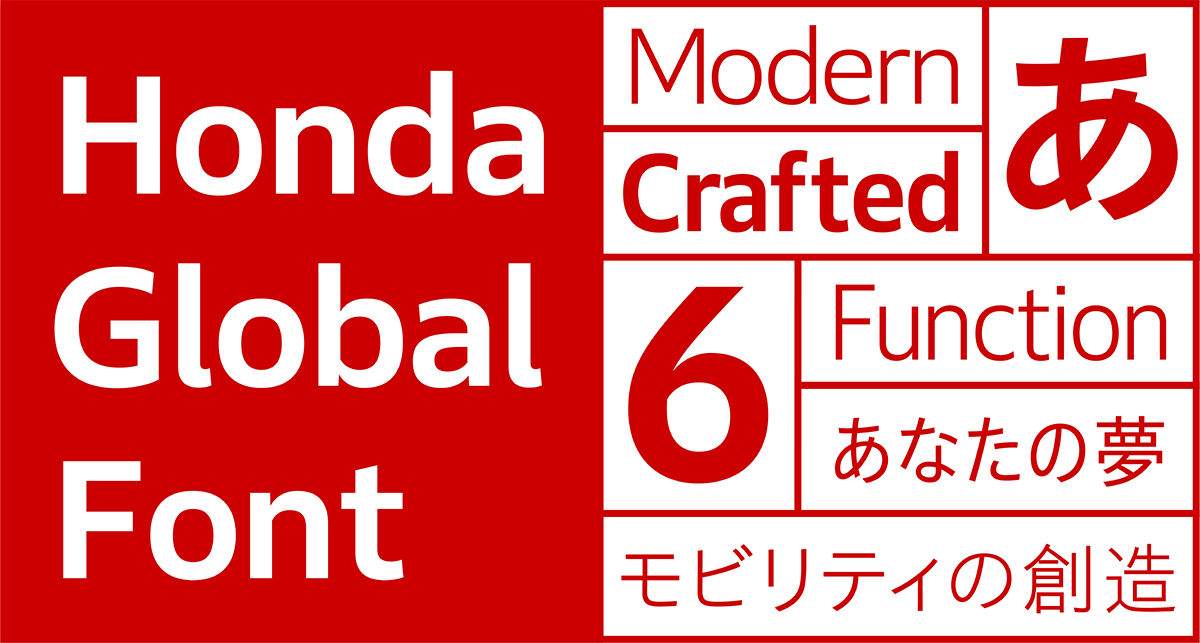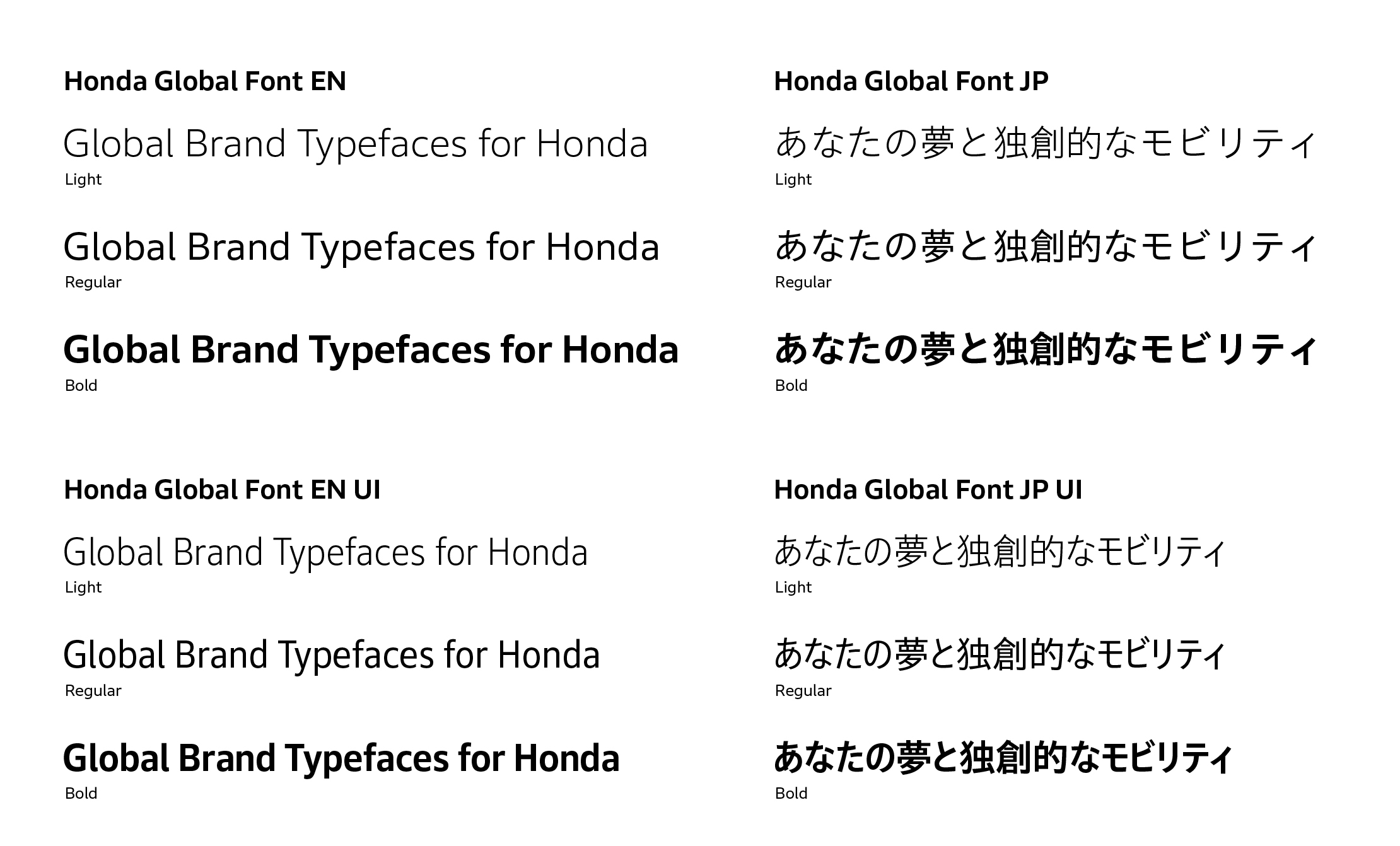
モリサワ 総合モビリティカンパニー Hondaのコーポレートフォント「Honda Global Font」ファミリーを開発
Hondaは、幅広いモビリティやサービスを世界中のお客様にお届けしている総合モビリティカンパニーです。100年に1度ともいわれる大きな変革期を迎えているなか、2001年に策定されたグローバルブランドスローガン「The Power of Dreams」を2023年に再定義し、改めて「Hondaのブランドマネジメントの起点」と位置付けました。夢のある商品・サービスをはじめとしたあらゆる企業活動を通して、この再定義に込めた想いを体現していくことで、よりHondaらしさを際立たせ、存在を期待される企業であり続けることを目指しています。
そして、このグローバルブランドスローガンを起点としたブランディングの一環としてコーポレートフォントの策定が検討され、多数のオリジナルフォント開発実績があるモリサワが、「Honda Global Font」ファミリーを開発・提供しました。「Honda Global Font」ファミリーの活用によって、Hondaブランドの発信の一貫性を高めるとともに、社内ブランディング意識の向上などが期待されています。
今回開発した「Honda Global Font」ファミリーは、欧文フォントの「Honda Global Font EN」と和文フォントの「Honda Global Font JP」、そして長体幅にしたUIフォントです。Hondaのブランドデザインを手掛けるブランド・コミュニケーションセンターのチームと、モリサワのプロジェクトメンバーが、両社の垣根を越えてアイデアを交わし合い、開発が進められました。
本フォントはHondaの人中心思想に基づいて、モビリティに求められる瞬間認知等の機能性を前提に、一人ひとりの強い意思を想起させるフォントとしてデザインされました。
欧文フォントのHonda Global Font ENは、モリサワの「Clarimo UD PE」をベースにカスタマイズしたサンセリフ体です。大きめの字面やオープンな開口部の処理によって、走行中での文字の瞬間的な認知のしやすさに配慮しています。また、安定感のある凛とした骨格と、勢いのある筆の運び、末端まで意識が通った丁寧な所作によって先進的かつこだわりを感じるモダンでクラフテッドな印象を作り出しています。
そして和文フォントのHonda Global Font JPは、モリサワの「あおとゴシック」をベースとしながら、有限会社字游工房の書体設計士 鳥海修氏が監修に携わり開発したゴシック体です。欧文と同じく視認性などの機能面に配慮しながらも、かなの横画に右上がりの傾斜を持たせることで、和文ならではの自然なリズムを表現しています。ストロークの抑揚と骨格には筆のニュアンスを取り入れて、一文字ずつに豊かな表情と引き締まった印象を持たせたフォントとしています。
完成した「Honda Global Font」ファミリーは現在、社内文書をはじめ名刺、封筒といったビジネスツールなどHonda社内におけるコミュニケーション領域で活用されています。今後は、さまざまなブランドコミュニケーションを通じて、対外発信でも標準フォントとして使用されるほか、製品のディスプレイやメーター、カタログなどにも順次搭載・使用され、運用が段階的に拡大する予定です。
本プロジェクトに関して、Hondaのコミュニケーションデザイナーである大石るみえ氏と字游工房の鳥海氏、およびモリサワのタイプデザイナーによる対談を実施しました。プロジェクトに込めた想いやデザインのこだわり、開発の舞台裏を語っています。